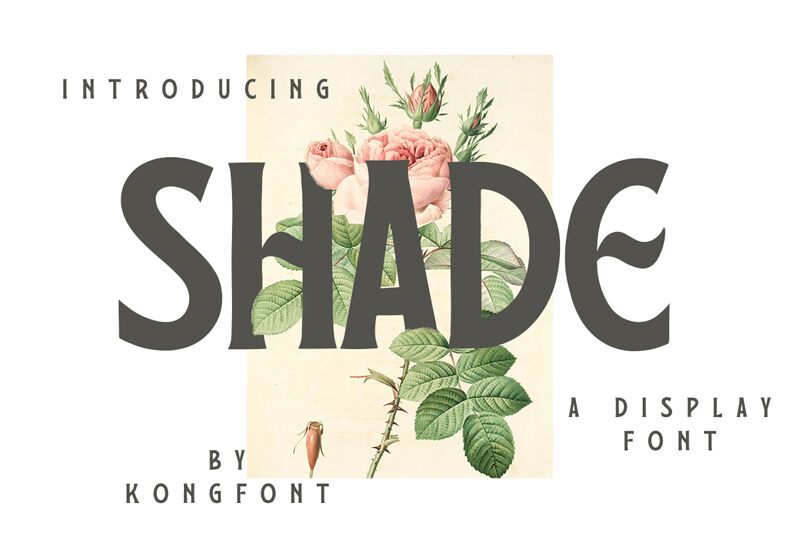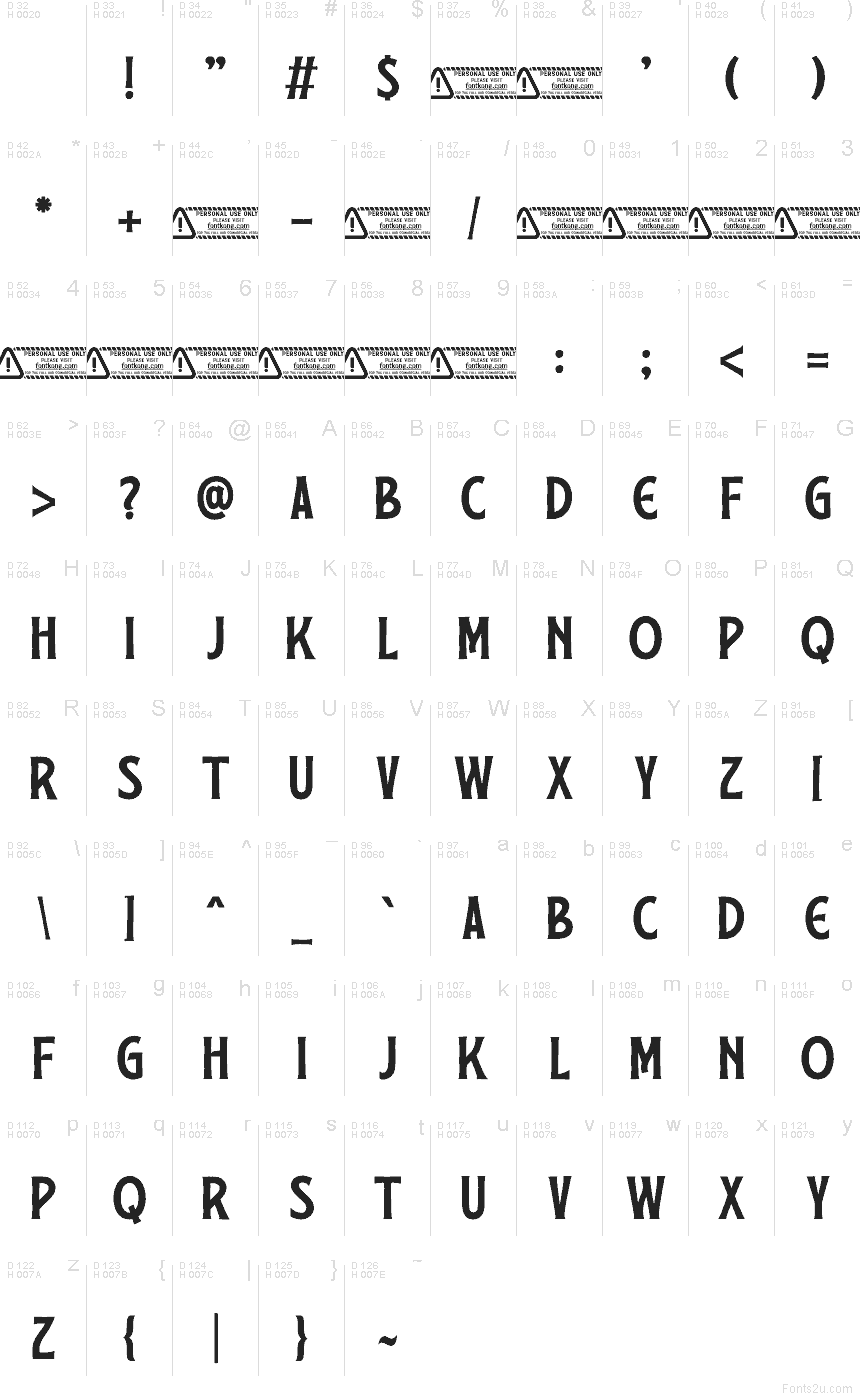
Shade od Kong Font to darmowy font retro typu display z wysokimi, kontrastowymi wielkimi literami, które nawiązują do klimatu plakatów z lat 70. Litery wydają się wąskie i dramatyczne, z ostrymi łączeniami w kształcie klina i szerokimi, zakrzywionymi liniami, które nadają słowom mroczny, teatralny charakter.
Idealnie sprawdzi się na okładkach albumów, w menu barów, na opakowaniach butikowych, w tytułach filmowych i nagłówkach w magazynach modowych, gdzie darmowy font z tak silnym klimatem epoki potrafi niemal samodzielnie stworzyć stylizację. Użyj go, gdy zależy Ci na tym, aby krótkie linie, napisy na okładkach czy inicjały typu monogram wyglądały elegancko, ale z nutką dekadencji; kontrast i skompresowany rytm sprawiają, że litery pozostają napięte i wyrafinowane.